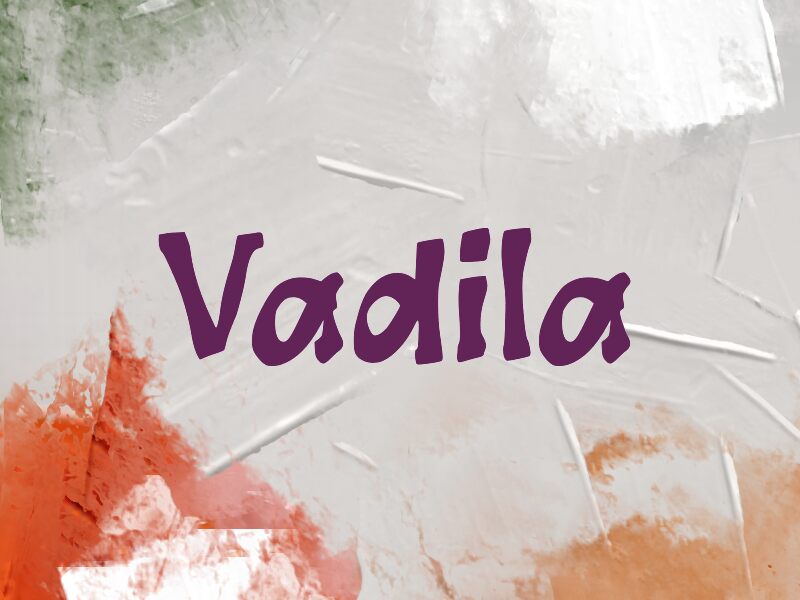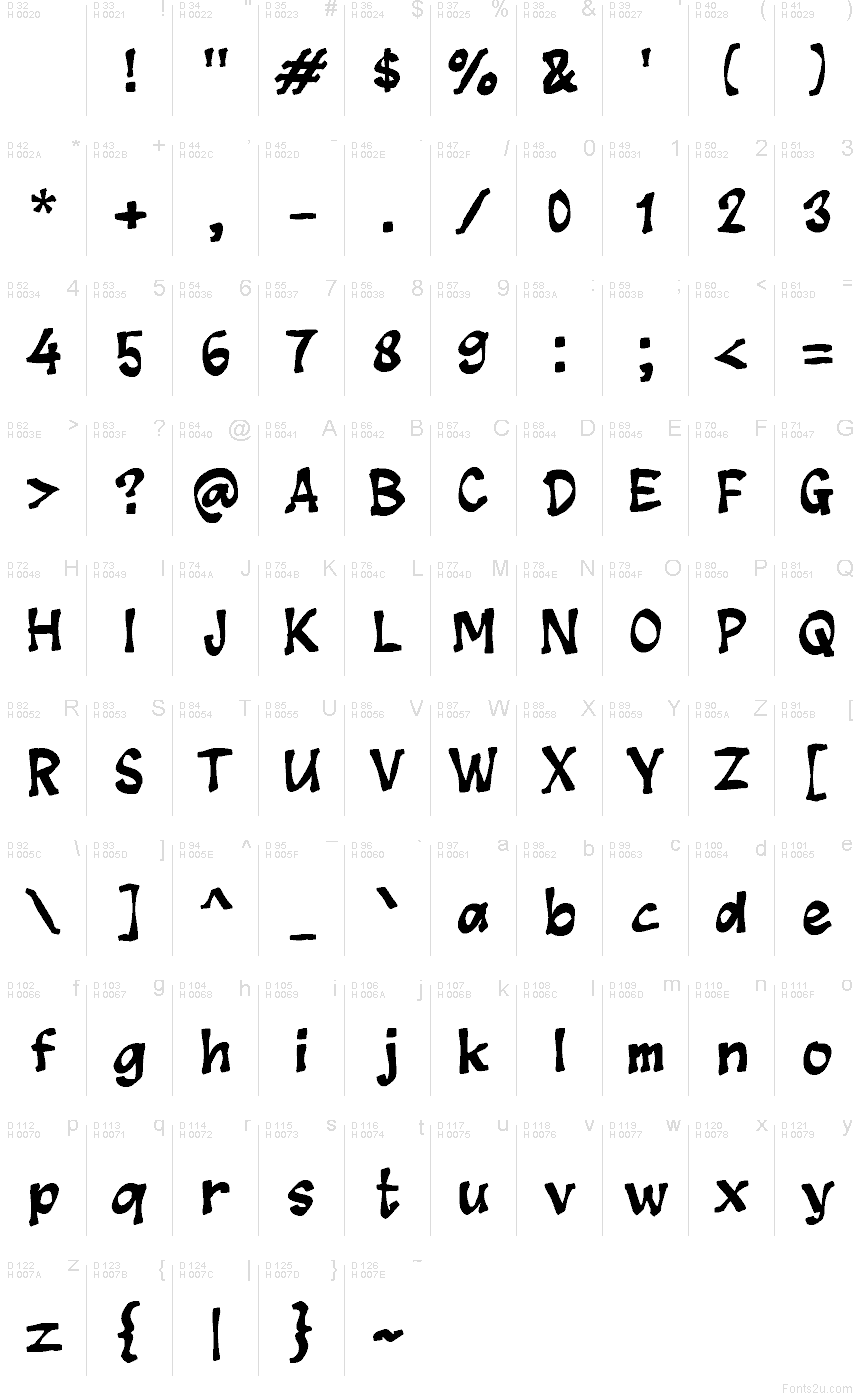
Vadila od Wep to darmowy, odręcznie rysowany font typu display o luźnym, nieoczywistym rytmie. Litery wyglądają, jakby zostały wycięte z miękkich kleksów tuszu – z pękatymi łukami, zwężanymi łączeniami i nierównymi górnymi krawędziami, co nadaje całości swobodnego, wręcz figlarnego charakteru.
Dzięki temu krój świetnie sprawdzi się na plakatach, okładkach zinów, w oprawie muzyki indie, na opakowaniach czy w projektach marek, w których zbyt czysta, geometryczna czcionka byłaby po prostu zbyt grzeczna. Jako darmowy font najlepiej sprawdza się w krótkich formach – nagłówkach, tytułach i logotypach – ponieważ to właśnie jego nieregularna sylwetka i dynamiczna kreska stanowią o jego sile.
Vadila
Prezentacja i próbka wizualna czcionki Vadila
Mapa znaków czcionki Vadila
Mapa znaków czcionki Vadila: Podstawowy łaciński, strona 1
Glify czcionki Vadila — Podstawowy łaciński, strona 1